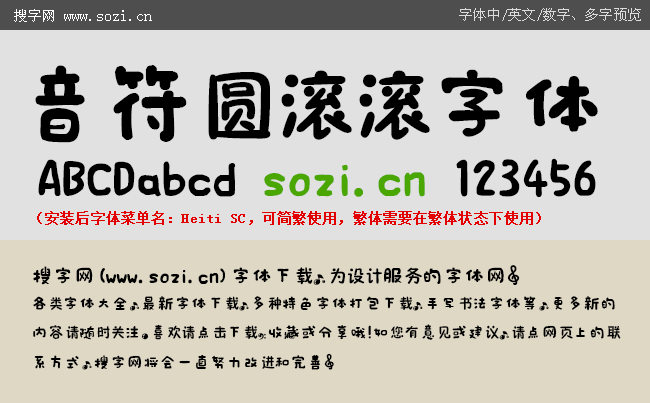
音符圓滾滾字體
搜字網(wǎng)給大家提供一款卡通手寫風(fēng)格的手機(jī)中文字體下載。名字叫音符圓滾滾字體,這款手機(jī)字體是仿照兒童手寫風(fēng)格的卡通手寫字體,結(jié)構(gòu)帶有POP字體風(fēng)格,字體間還插入了卡通音符圖案,特別適合喜歡手機(jī)字體個性一些的朋友在手機(jī)上安裝使用。